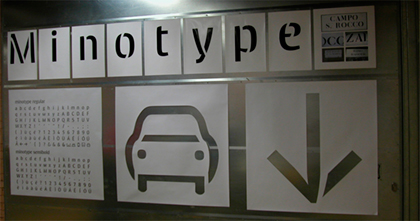
Luciano Perondi chez Molotro (type design) via Velvetyne
Stencil typeface Minotype (alias Ninzioletto), designed by Luciano Perondi
Toujours via Velvetyne (curiosités typographiques) je découvre ce stencil très enlevé, le Minotype (allusion à Monotype qui se caractérise par le design de bas de casses assez rares dans ce type de création. L’orginalité (entre autres) de l’alphabet tient à l’attaque en oblique des stries dans les lettres, contrairement au Stencil Glaser (magnifique) qui était sans nuance, tout en verticalité. Project directed by Leonardo Sonnoli, for VivereVenezia3.